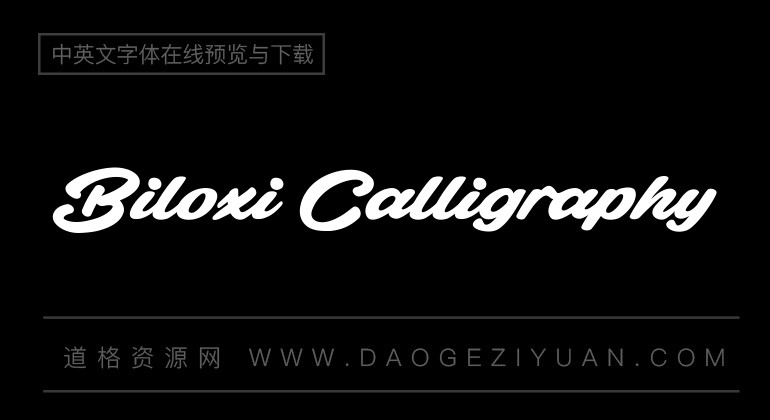
Biloxi Calligraphy
? Biloxi Calligraphy 是一款具有传统书法风格的字体,由美国设计师John Stracke设计。它具有高度可读性,自然的节奏感和温暖的气氛,可以为文案增添更多的艺术气息。它有着清晰的笔画,自然的流动感,以及细节丰富的设计,能够给文案带来更多的艺术气息。
Biloxi Calligraphy是一款非常不错的手写艺术字体,具有很好的视觉感,适合于文化类的宣传设计、商业类品牌的广告和产品包装设计以及个性化文字排版等较多场景。